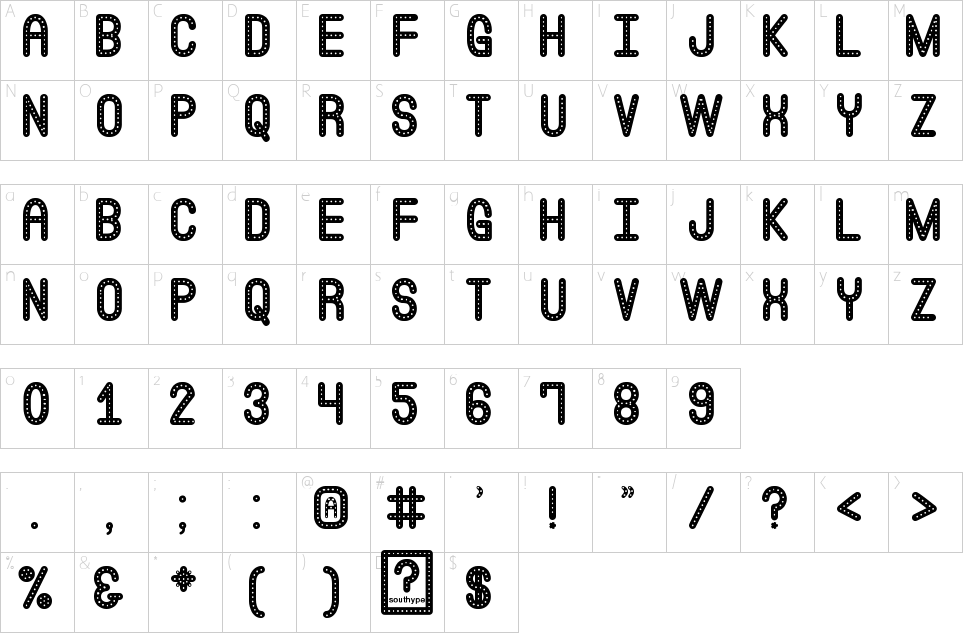
Aqui está uma descrição em português do Brasil, envolvente e natural, para uma página de download da fonte ‘Eat at Joe’s St Font’: A fonte ‘Eat at Joe’s St Font’ é um estilo casual e alegre, perfeito para criar textos que sejam leves e descontraídos. Essa fonte foi desenhada pelo designer Southype e já foi baixada mais de 141.668 vezes. Perfeita para aplicações em sites, e-mails, postagens no Instagram ou qualquer formato de conteúdo digital, a ‘Eat at Joe’s St Font’ oferece um charme autêntico e uma pitada de humor que enriquece seu design. Com seu design suave e versátil, esta fonte é um marco para qualquer projeto de design gráfico que busca trazer um toque único e divertido.